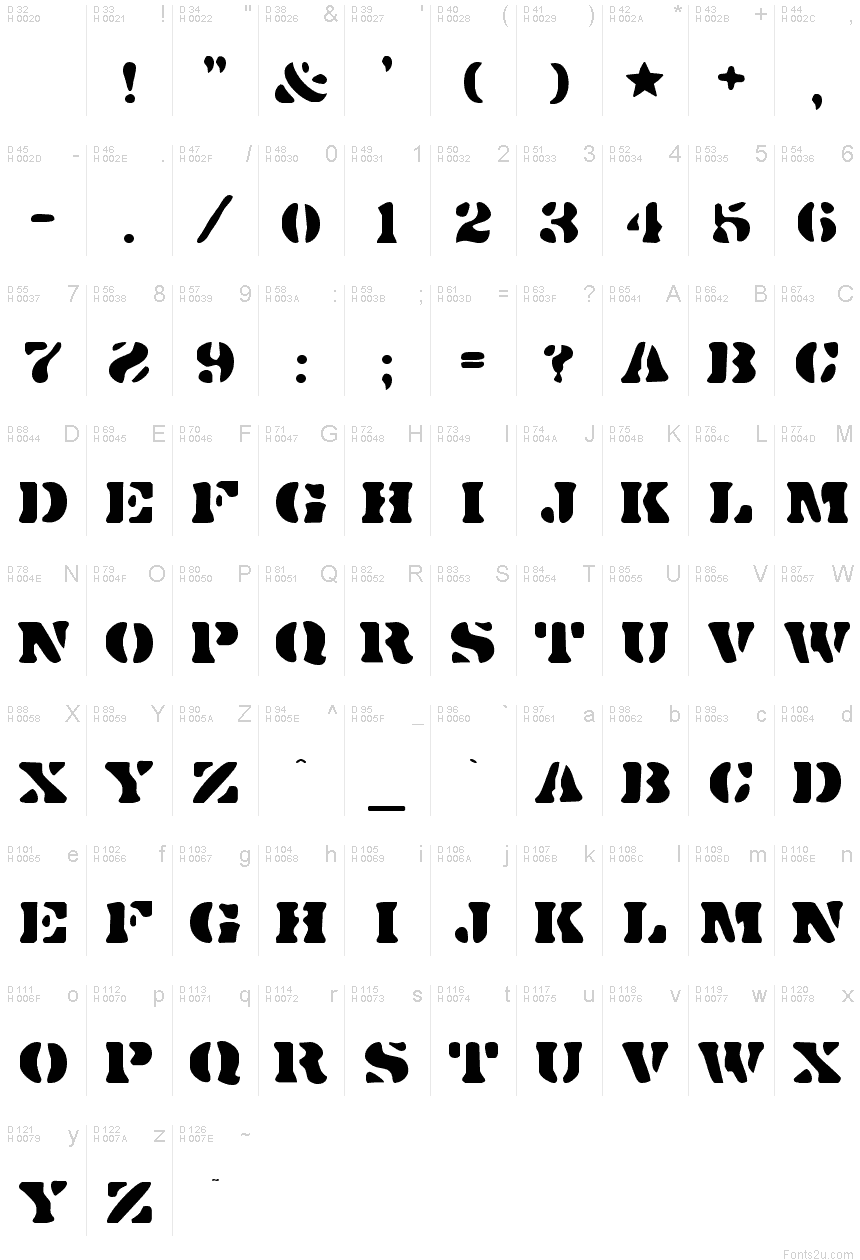
Dirty Baker's Dozen od Ray Larabie to darmowy, dekoracyjny krój typu display o brudnym, oldschoolowym charakterze. Jego masywne, szablonowe kształty wyglądają, jakby zostały wycięte z gęstego tuszu, tworząc odważne sylwetki i nietypowe wycięcia wprost z pogniecionego plakatu koncertowego. Ciasne światło sprawia, że słowa są zwarte i wyraziste, więc nagłówki uderzają z siłą pieczątki wbitej w papier.
Użyj Dirty Baker's Dozen, aby podkręcić energię na plakatach koncertowych, zinach, grafikach na koszulki, w brandingu deskorolkowym czy tatuażowym, szyldach barowych i opakowaniach w stylu retro. Ten darmowy font błyszczy, gdy jest użyty w dużej skali; zestaw go z czystym, neutralnym krojem bezszeryfowym w tekście głównym, aby litery o szorstkich krawędziach pozostały w centrum uwagi.